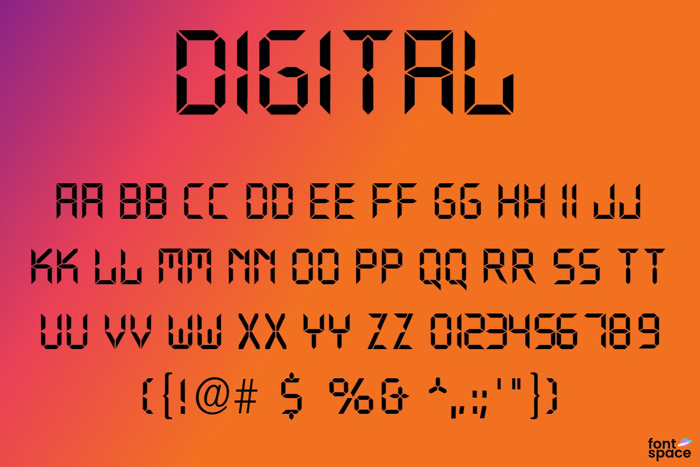
Digital Font
Die Schriftart wurde von Allen R. Waldens Crystal font abgeleitet. Da auch diese komplett Freeware ist, wird diese Schriftart ebenfalls als Freeware für den privaten und kommerziellen Gebrauch angeboten. Sie wurde um die Kleinbuchstaben (Ebenfalls groß) erweitert und ist nicht kursiv.
The font was derived from Allen R. Walden Crystal font. Since this is completely freeware, this font is also available as freeware for private and commercial use. It was the lowercase letters (also large) extended and is not in italics.